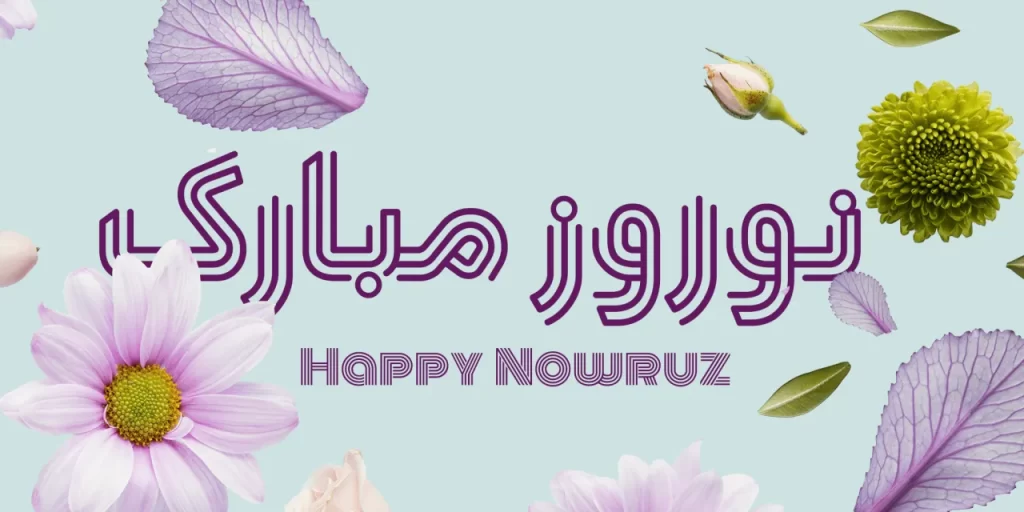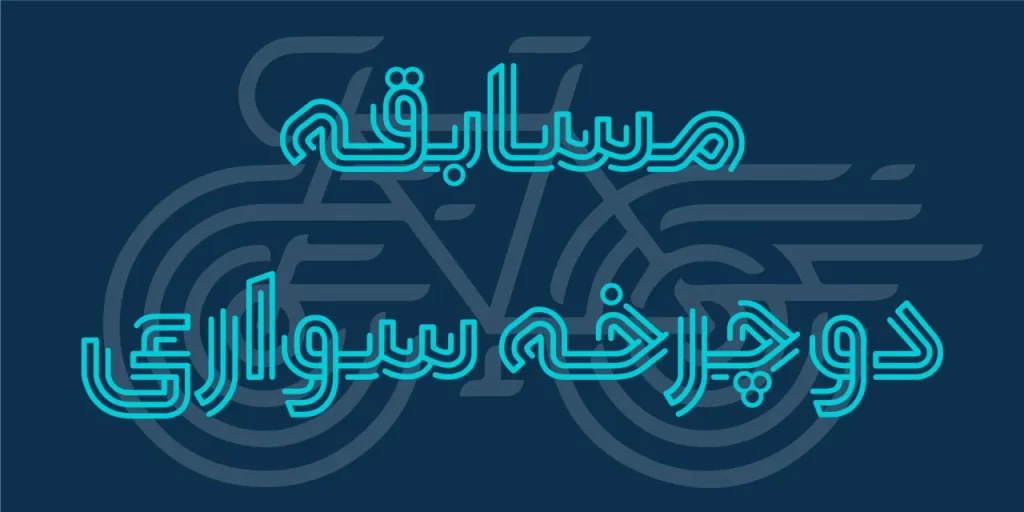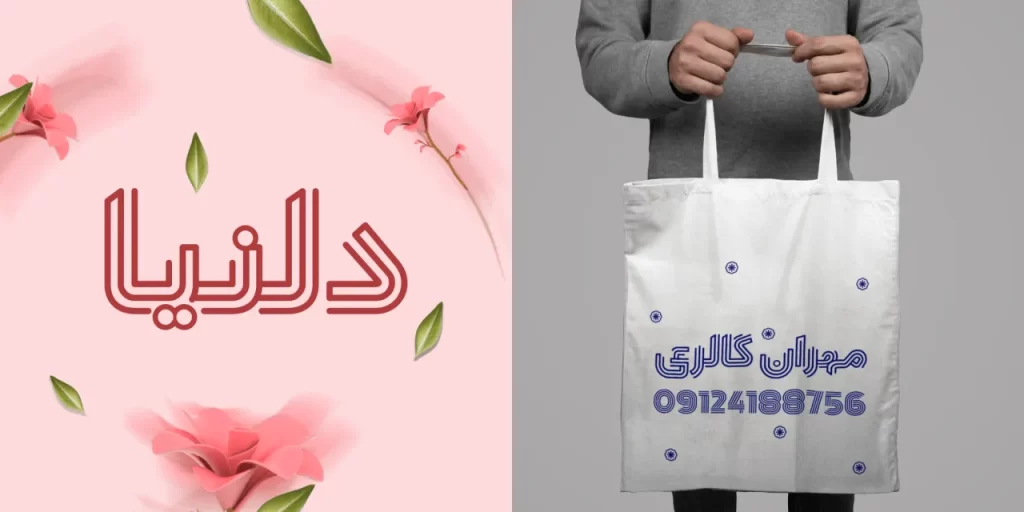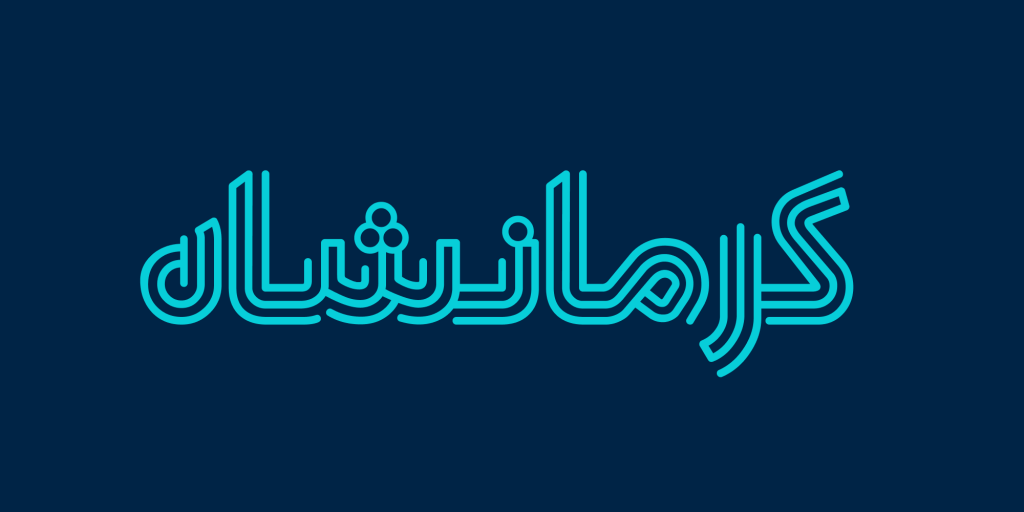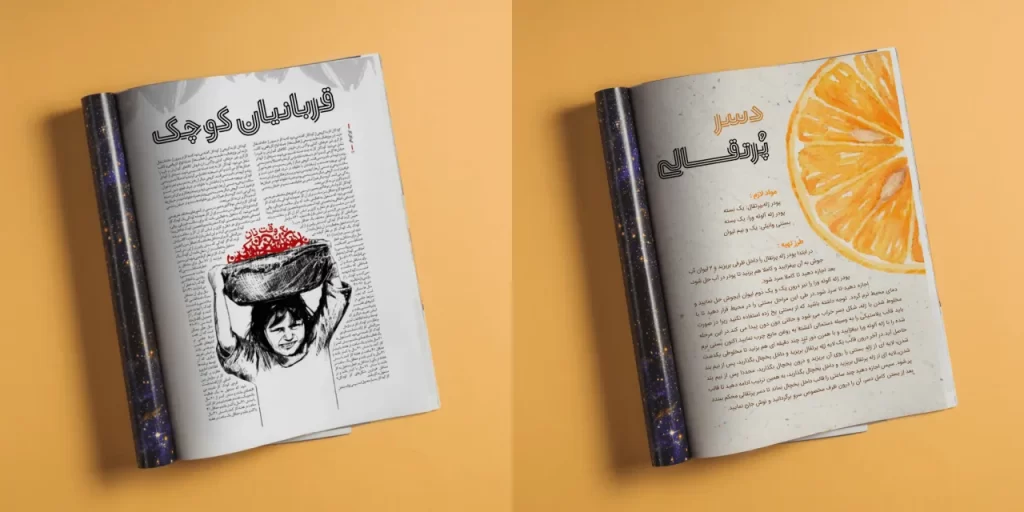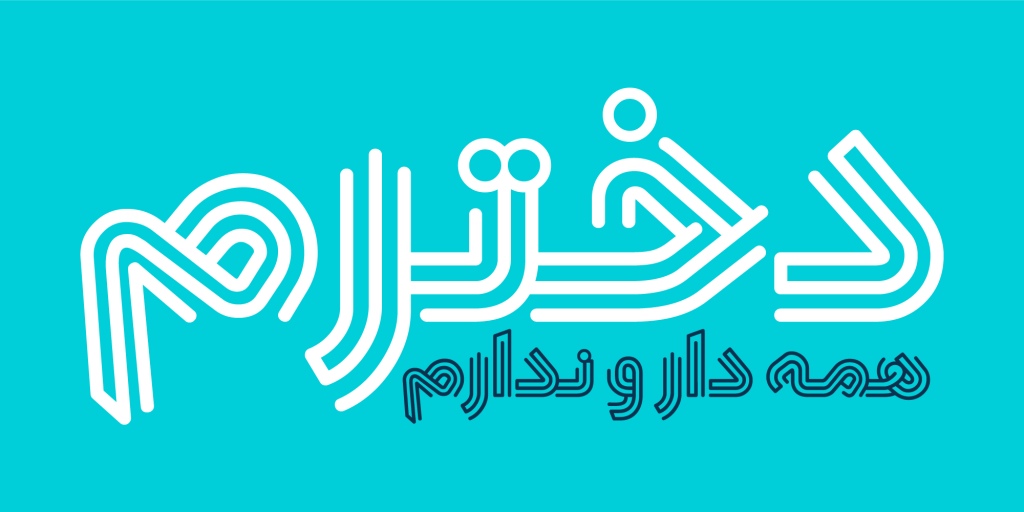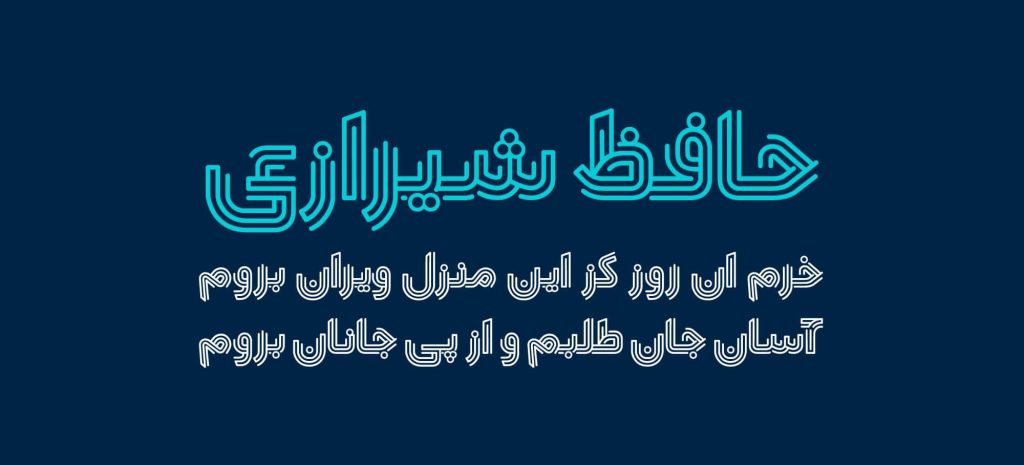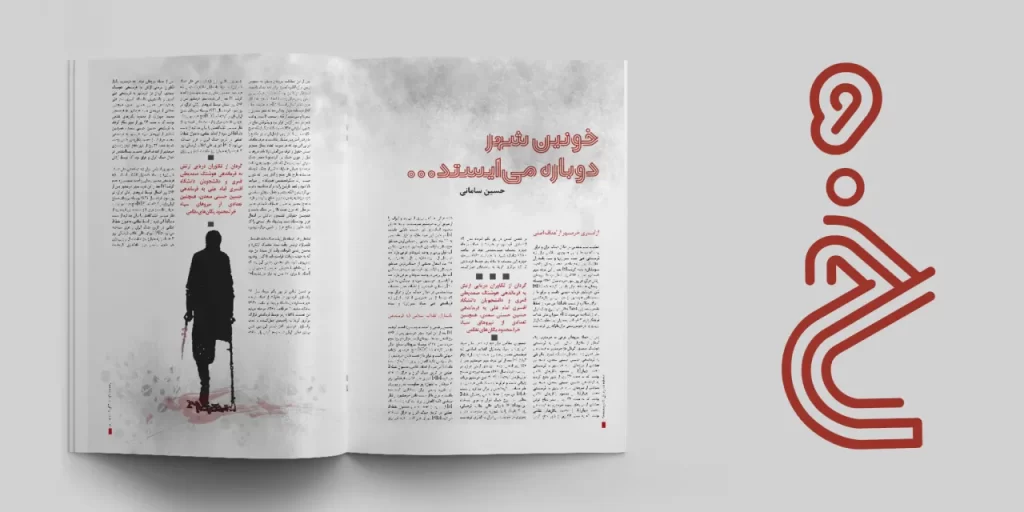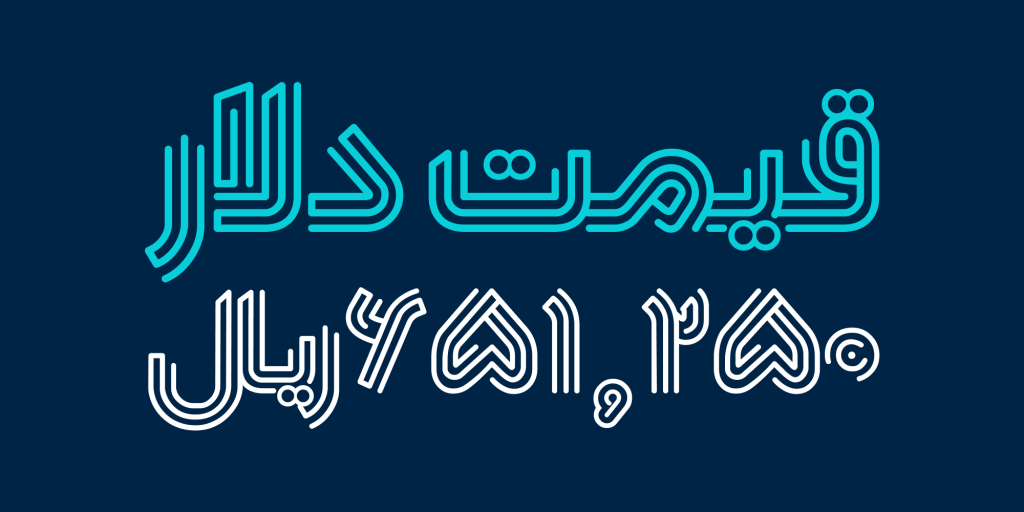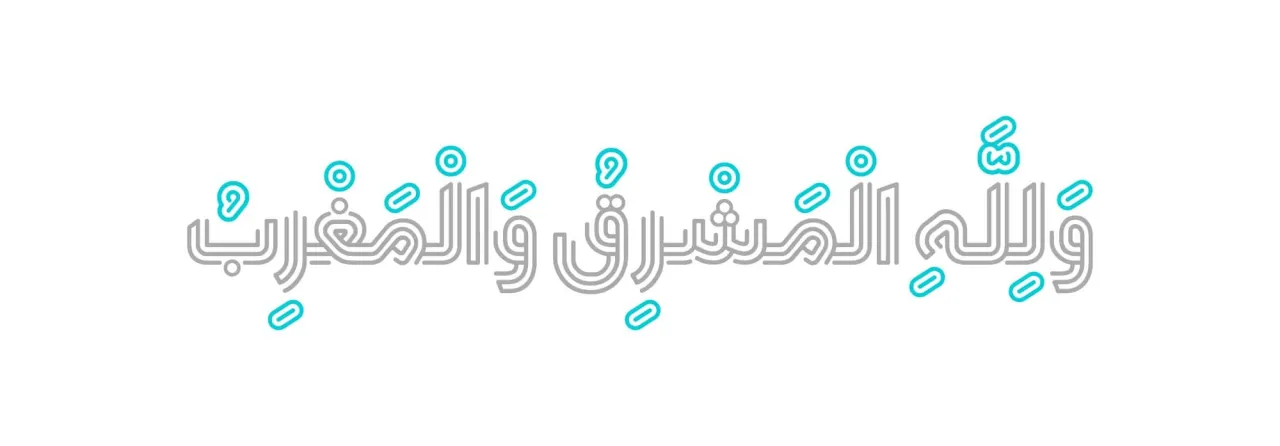
فونت دلنیا
فونت دلنیا، تایپ فیسی با فرم های طراحی منحصر به فرد است. از مهمترین ویژگی های این قلم می توان به بالا بودن ویژگی نمایشی و تزئینی آن اشاره کرد. ساخته و متولد شده است تا نگاه ها را به خود کشانده و تسخیر کند. از همین ذو مناسب متون کوتاه و عناوین و تیتر های جذاب و تبلیغاتی است.
یکی از اهداف طراحی دلنیا رسیدن به قلم و تایپ فیسی بوده که قادر به ماندگاری مطالب و محتوا ها در ذهن شود. به عبارت دیگر به وسیله ایجاد نوعی از فرم های طراحی که سبب ایجاد مکث و عمیق خواندن برای مخاطبین می شود محتوا و مطالب را در ذهن خوانندگان مانا و ماندگار می کند.
قلم دلنیا و تاثیر بر ذهن خوانندگان
با توجه به نوع ساختار طراحی در این تایپ فیس و همچنین فضاهای مثبت و منفی و گردش حروف فارسی این فرصت و امکان به مخاطب و خواننده داده شده که ذهن او فرم حروف را تکمیل نماید. این ویژگی منجر به ایجاد مکث و افزایش زمان خواندن، جهت مطالعهی محتوای مورد نظر می شود و در نتیجه محتوا نیز در ذهن ها به کمک این نوع از طراحی ماندگارتر میشود.
به عبارت دیگر می توان این گونه تصریح کرد که که شکل دیداری فونت علاوه بر تسهیل در امر خوانش میبایست در پردازش و ماندگاری آن نیز نقش داشته باشد. و دلنیا از با ایجاد مکث و طمانینه تمرکز خواننده بر محتوای ارائه شده است تا با صرف زمان بیشتر اطلاعات در ذهن مخاطبان ماندگار شود.
ازنظر کاربردی می توان از دلنیا در طراحی تیترهای بلند و کوتاه عناوین جذاب و تبلیغاتی و پوستر و مقالات علمی آموزشی و … بهره مند شد .دلنیا دارای روحیه و شخصیتی به روز پرانرژی و فعال و جوان است که علاوه بر زبان فارسی از زبان های کردی و عربی نیز پشتیبانی می کند.
فونت دلینا براساس آزمون لغات در گروههای سنی مختلف مورد آزمایش قرار گرفت و نتیجه آزمایش فوق مطالب پیشین را تأیید نمود.
از نقطه نظر کاربردی، فونت دلنیا به منظور استفاده در تیترهای بلند و کوتاه طراحی گردیده است. در این قلم سعی بر آن گردیده که شکل متصل و منفصل حروف یکسان باشد و به حداقل رساندن خطوط کرسی در کلمات مُنجر به نظم بصری بیشتری در جملات شده است.